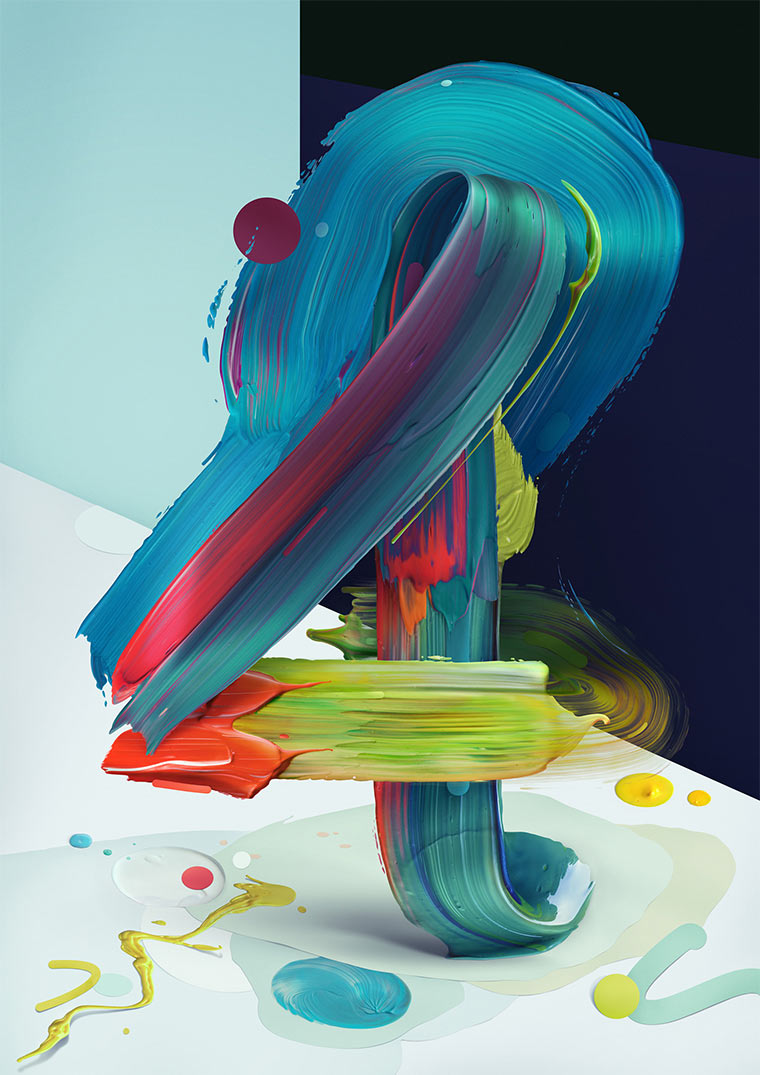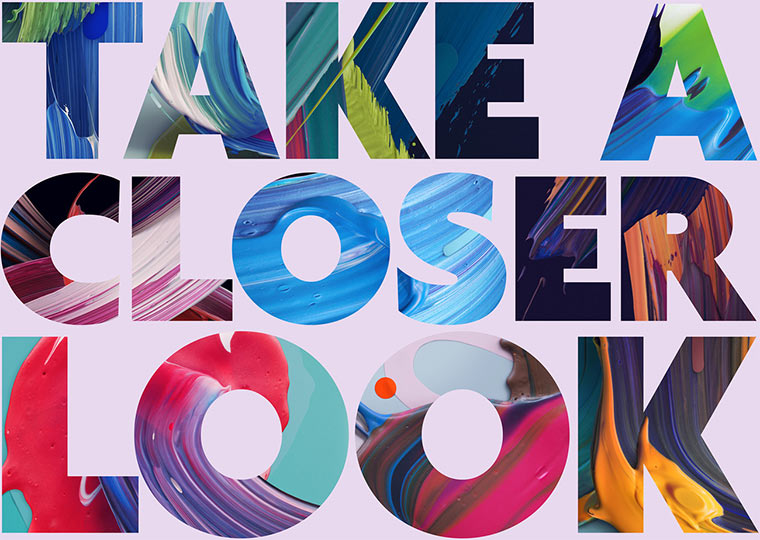
Kreative Kunst von Pawel Nolbert
Gemalte 3D-Typografie
Gemalte 3D-Typografie Atypical_01
Pawel Nolbert beschreibt seine künstlerische Darstellung in der Serie Atypical selbst als „half-realistic, half-illustrative figurative sculptures“. Irgendwie zwischen Malerei, Typografie und Skulptur befinden sich seine Werke, die teils räumlich, teils flat erscheinen. Durch bemalte und arrangierte Folien(röhren) schafft er es, die Farbe in die Vertikale zu ziehen. Jedenfalls eine sehr ungewöhnliche und kreative Mischung, die einzigartige Eindrücke vermittelt.
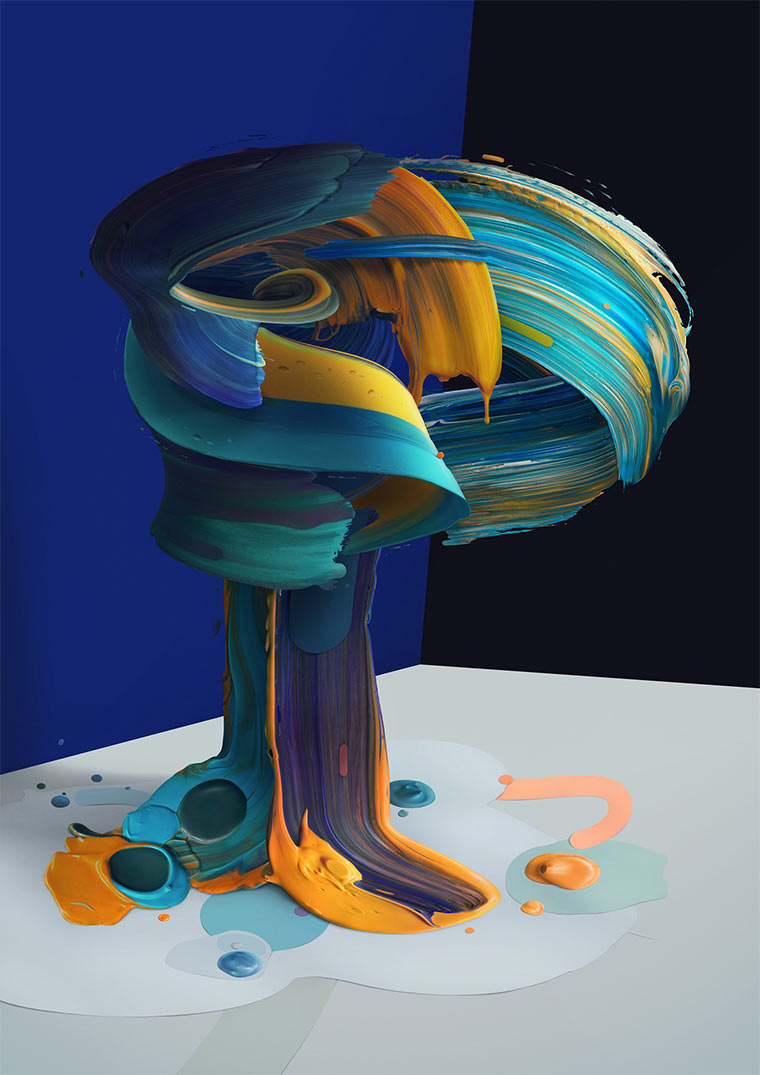
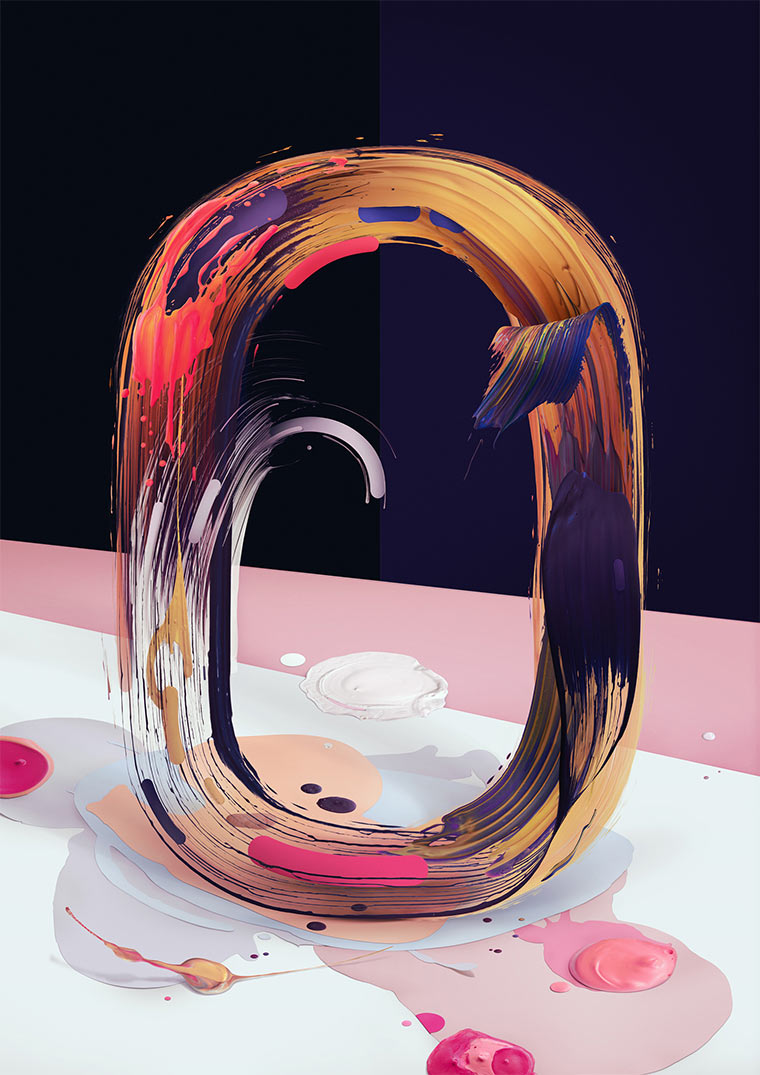
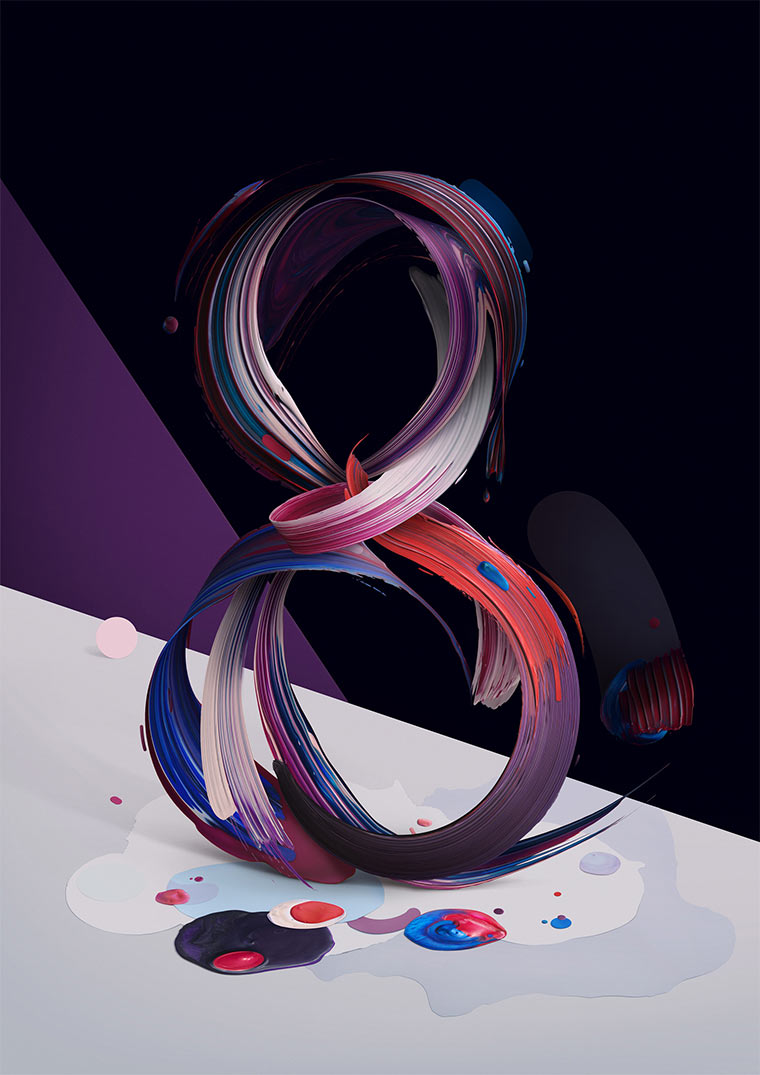Gemalte 3D-Typografie Atypical_02
Gemalte 3D-Typografie Atypical_03
Gemalte 3D-Typografie Atypical_04
Gemalte 3D-Typografie Atypical_05
Gemalte 3D-Typografie Atypical_06
Gemalte 3D-Typografie Atypical_07
Gemalte 3D-Typografie Atypical_08
Gemalte 3D-Typografie Atypical_09